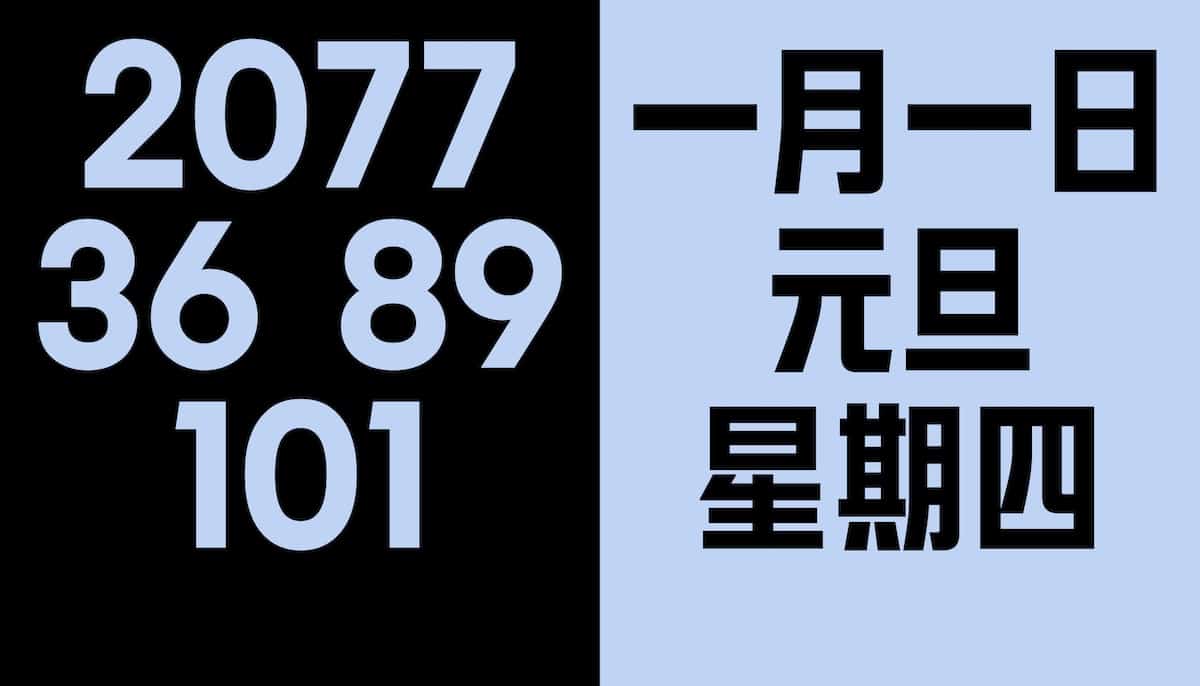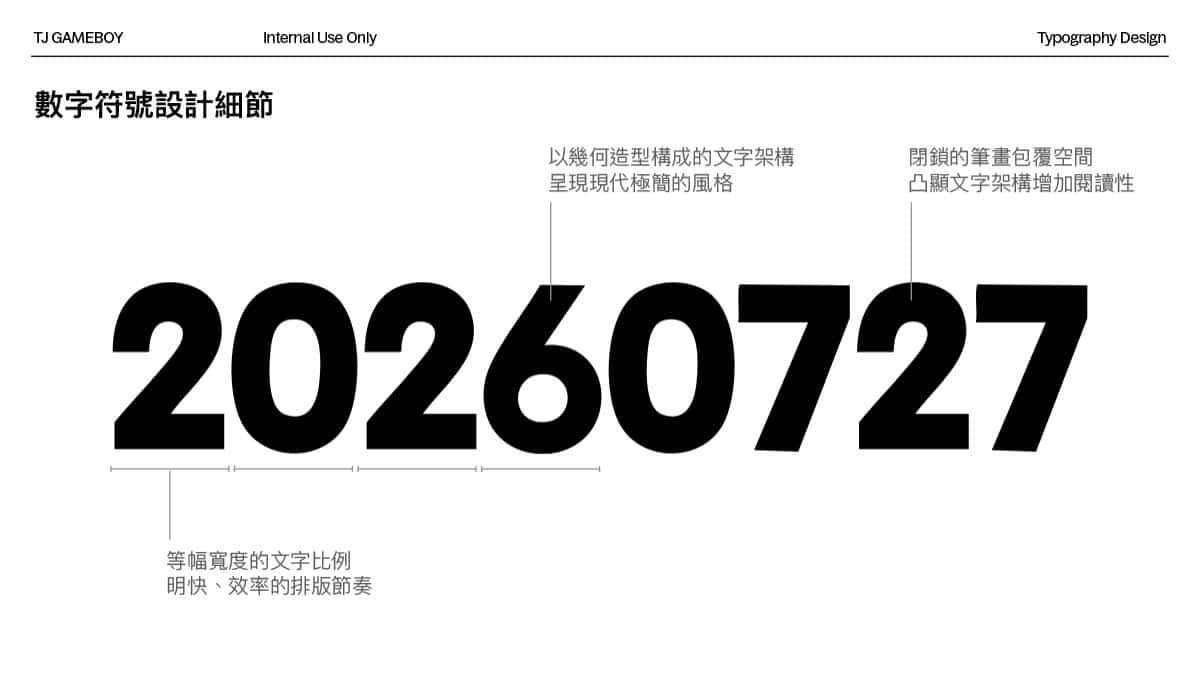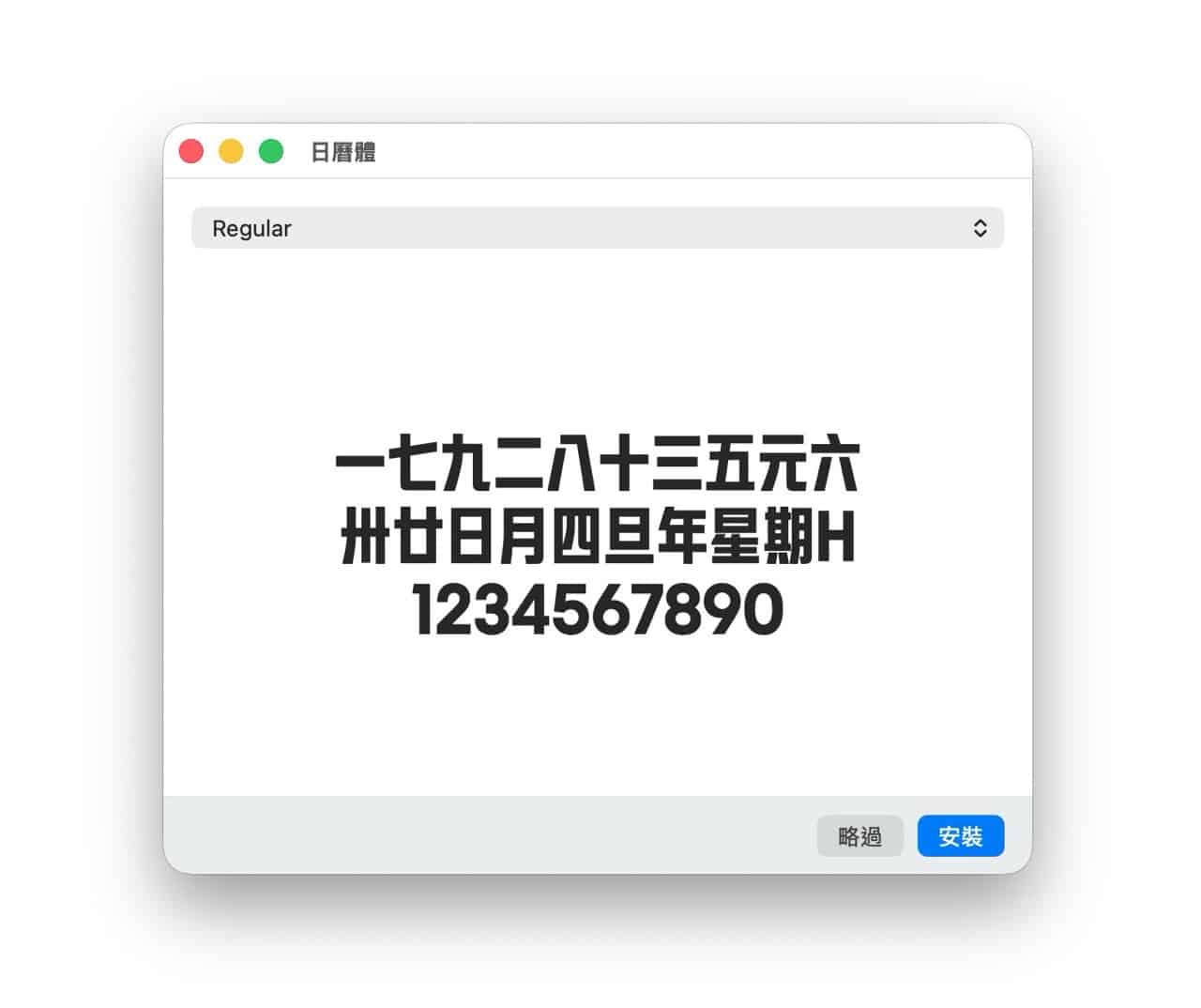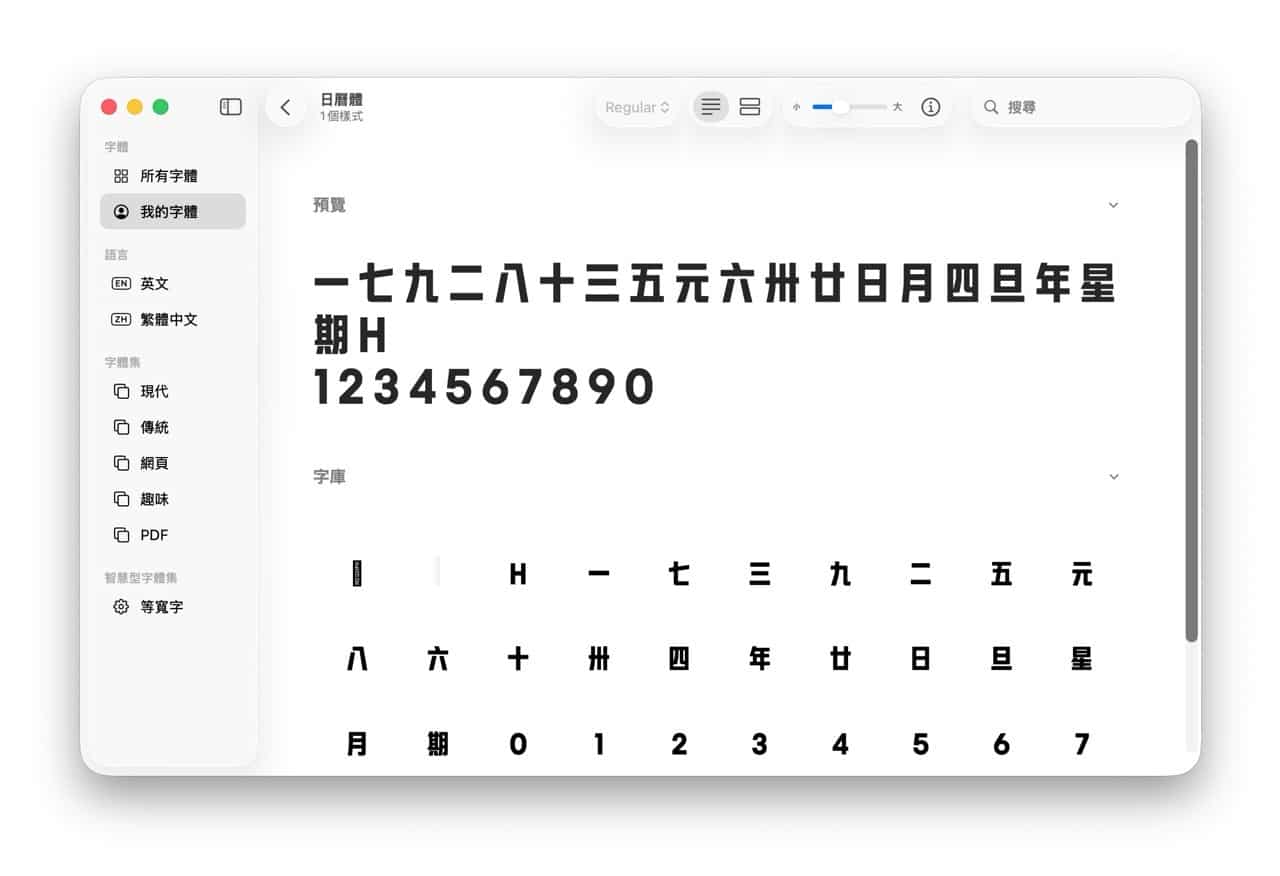
最近無意間發現一款台灣的日曆字型「日曆體」,看了背景介紹覺得很有趣,以往大家會看到的手撕日曆其實沒有專屬字體,通常會使用粗黑體,畢竟日曆的主要用途還是要能輕鬆看到日期等資訊,並不會考慮近看的細節,因此有非常多設計上的「瑕疵」存在許久。但也因為日曆每天都要被撕掉,大多數的人不會重視這些設計,於是就這麼過了數十年,這也成為台灣日曆專屬的一種味道。
從《共編曆》計畫誕生的開源字型
一家在台中經營超過五十年的日曆印刷工廠推出一項名為《共編曆》的計畫,簡單來說,他們找來 300 多位網友「共同編輯」日曆,為每一天都加入一個獨特故事,過日子還能細細品味其他人生命中可能最難忘的一天,使日曆直接提升到另一層次(同時加入非常巧妙的設計)。
開發共編曆的過程中,團隊決定「共享」讓這項計畫更完整,於是開發出台灣第一套屬於所有人的日曆字體,讓日曆也能有專屬字型,而這款「日曆體」將開放給所有人免費下載使用!無論設計、創作或是各種用途皆可,個人和商業用途都沒問題。
開啟「日曆體」的開發說明文章後會看到字型的開發背景和特色等說明,其中也會有該字型的預覽和設計師等資訊,這款字型是與字體設計師泰江合作,主要是改善傳統日曆的辨識性,也就是無論遠看或是近看都能取得一定程度的平衡(傳統日曆只有遠看可以,近看很醜)。
細節部分可參考以下我從文章轉貼的圖片,日曆體只有少部分的字元,包括阿拉伯數字、中文數字和星期月份等,無法成為完整的中文字型使用,不過如果剛好只需要數字的話就很適合。